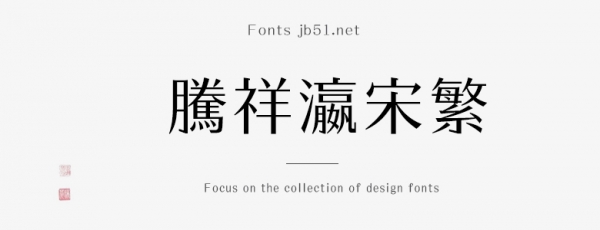
騰祥瀛宋繁-W3是一款不錯的藝術字體,由騰祥字庫出品,此款字為瀛宋W3,結構端正、重心平穩(wěn)、美觀實用,具有很好的視覺感,適合應用于藝術設計、平面宣傳設計、網頁設計,書法字帖等領域,需要的朋友可以前來本站下載。
此款字為騰祥瀛宋系列字庫,是騰祥公司自主精心設計開發(fā)的正文字體。一共有10款粗細,以期滿足用戶不同領域的用字需求。此款字為瀛宋W3,可用于正文、小標題等。整個系列字庫風格完全一致,不管是常用字或是非常用字,字字精美、結構端正、重心平穩(wěn)、美觀實用。此款字為騰祥公司推送《2019森澤字體大賽》參賽作品。